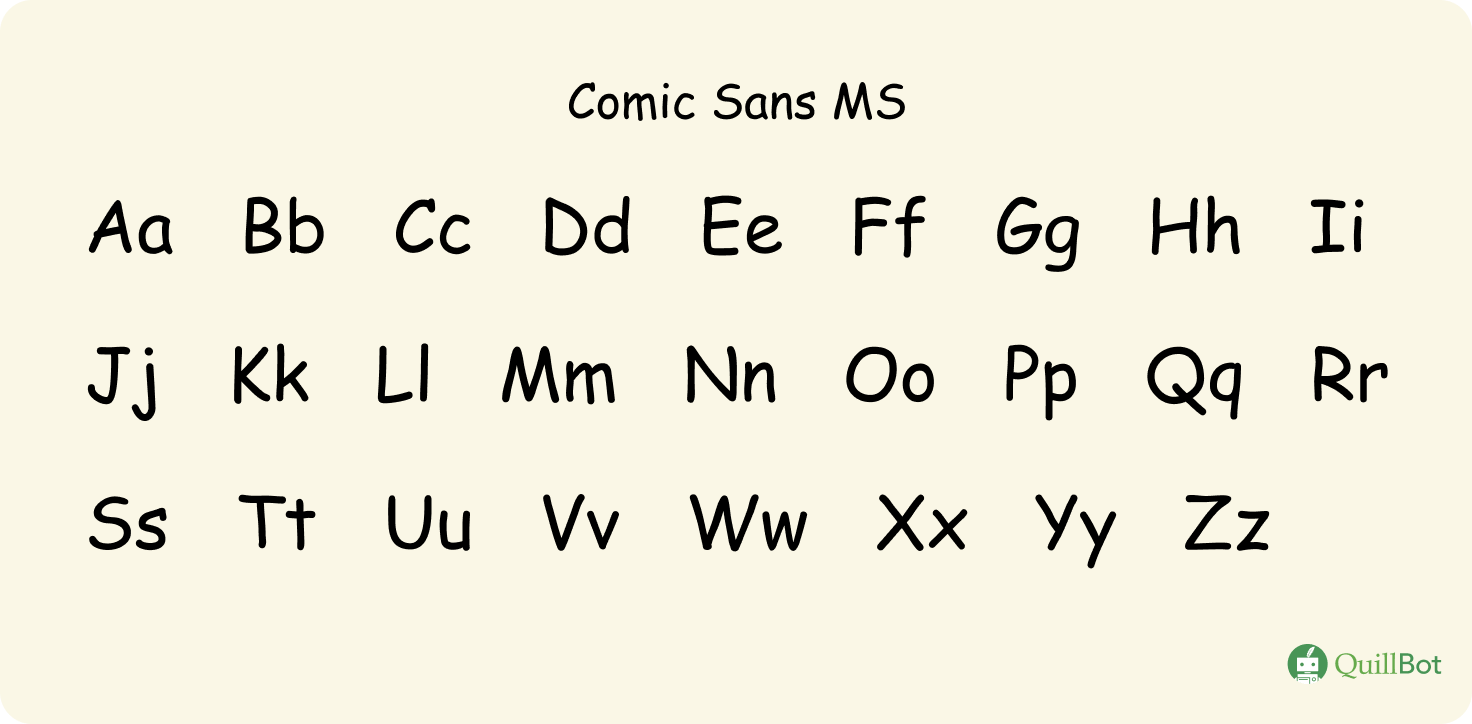
Comic Sans MS | Une police souvent moquée, mais jamais égalée
On l’aime ou on la déteste — souvent les deux à la fois, d’ailleurs —, mais une chose est sûre : Comic sans MS est une police qui ne laisse personne indifférent.
Et pour cause, il ne s’agit pas vraiment d’une police de caractères comme les autres, mais d’un véritable phénomène culturel, qui a notamment marqué la pop culture (ou culture de masse) des années 2000 et 2010.
Mais si, souvenez-vous…
- Année de création : 1995
- Pays de création : États-Unis
- Créateur : Vincent Connare (pour Microsoft)
- Type de police/Classification VoxAtypi : Manuaire
- Type d’empattement : Sans empattement (sans serif en anglais)
- Popularité : + (très répandue et plébiscitée à une époque, mais souffre désormais d’une réputation désuète et peu professionnelle)
- Image véhiculée : Informelle, ludique, décontractée, « cartoonesque » voire amatrice et dépassée.
- Point d’attention particulier : Facilite la lecture aux personnes atteintes de dyslexie.
À l’instar de toute tendance sociétale, Comic Sans MS compte bien sûr son lot de détracteurs, voire de haters fièrement autoproclamés, parmi lesquels la police du « mauvais goût typographique ».
Certes, Comic Sans MS n’est pas tracée dans les lignes les plus fines et on la verrait mal figurer en page de garde d’une thèse académique, mais elle n’en reste pas moins un symbole évocateur d’un esprit récréatif et d’une époque ultra-créative.
Quant à l’utiliser aujourd’hui, c’est encore possible, mais à moins de l’envisager pour un mème, la prudence est de mise. Attention en effet à ne pas vous emballer sous l’effet de la nostalgie…
Police Comic Sans MS : histoire et développement
Le premier adjectif qui vous vient en songeant à Comic Sans MS est « cartoonesque » ou enfantin ? Rien de plus logique là-dedans, puisque c’était le but recherché à l’origine !
En 1994, Vincent Connare (amis francophones, prière de veiller à bien orthographier son nom pour éviter toute confusion malencontreuse…), typographe chez Microsoft Corporation, se voit confier une mission de la plus haute importance : élaborer la typographie d’un nouveau logiciel.
Le nom de l’heureux élu n’est autre que Microsoft Bob, un programme pensé sur le papier pour proposer une interface non technique aux tout nouveaux utilisateurs d’ordinateurs de bureau.
Cela ne vous dit peut-être rien à première vue, mais cela n’est guère étonnant : Bob a fait un bide monumental, conduisant à l’abandon du projet avant même la sortie de Windows 98.
Selon le Time, au-delà de l’échec du logiciel, le grand tort du projet est d’avoir permis… la naissance de l’horrible police Comic Sans MS.
Persécution gratuite, vous dites ?
Aussi, afin de rendre justice à ce cher Bob parti trop tôt, rappelons tout de même que, si l’idée mère est rapidement morte dans l’œuf, elle a mis le pied à l’étrier à la conception de Rover, le petit chien d’aide à la recherche qui a accompagné (avec succès !) les utilisateurs de Windows XP durant de nombreuses années…
Parmi les utilisateurs visés par Bob figuraient les enfants. Comic Sans MS a de ce fait été conçue pour donner un côté ludique à l’interface du logiciel, dont l’esthétique n’était pas sans rappeler celle des dessins animés de l’époque.
Quand on y pense, son nom (le nom Comics étant en anglais l’équivalent de bande dessinée en français) est d’ailleurs plutôt transparent quant à ses intentions…
Intégrée par défaut dans Windows malgré la mise au rebut anticipée de Bob, Comic Sans MS séduit le grand public pour son aspect informel, à tel point qu’on la retrouve très vite partout où l’on va, y compris en dehors des murs de la Toile : affiches scolaires, faire-parts, panneaux de rue, présentations PowerPoint, sites web des années 2000… Sa disponibilité quasi universelle et ses accents décontractés en font le choix par défaut de millions d’utilisateurs non professionnels, à commencer par les jeunes.
Dans le monde francophone, à la fin des années 2000, les Skyblogs des ados d’alors arborent des centaines de milliers de « Lâââch3 té comZZZZZ » stylisés en police Comic Sans MS, que l’on retrouve alors également dans les statuts personnalisables du logiciel de messagerie instantanée MSN.
C’est précisément son omniprésence, combinée à des usages bientôt considérés comme futiles et déjà dépassés, qui va sceller sa réputation…
Ne s’agit-il pas après tout du lot de nombreuses tendances populaires ? Elles deviennent un beau jour désuètes, puis, beaucoup plus tard, on leur concède, presque à la manière d’un euphémisme, un petit côté vintage…
Une technique maintes fois répétée, qui a fait ses preuves y compris chez les plus pointilleux…
Après tout, si vous êtes bloqué, que pouvez-vous perdre à essayer ?